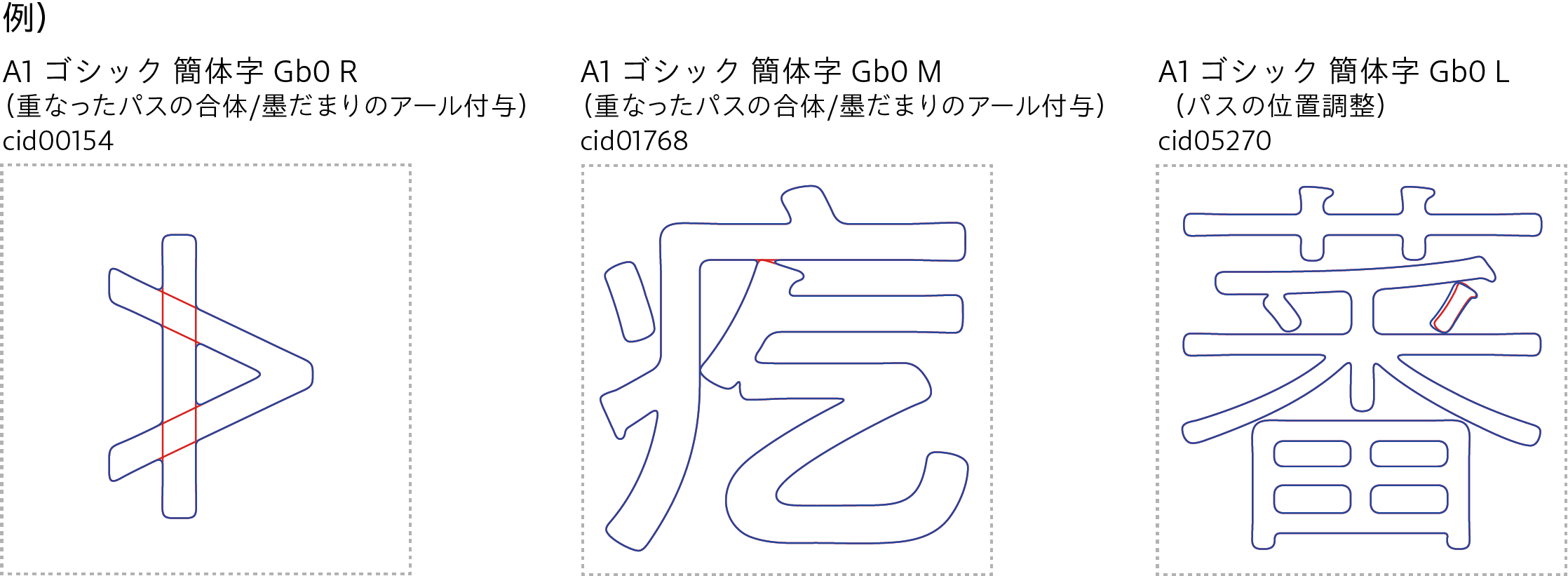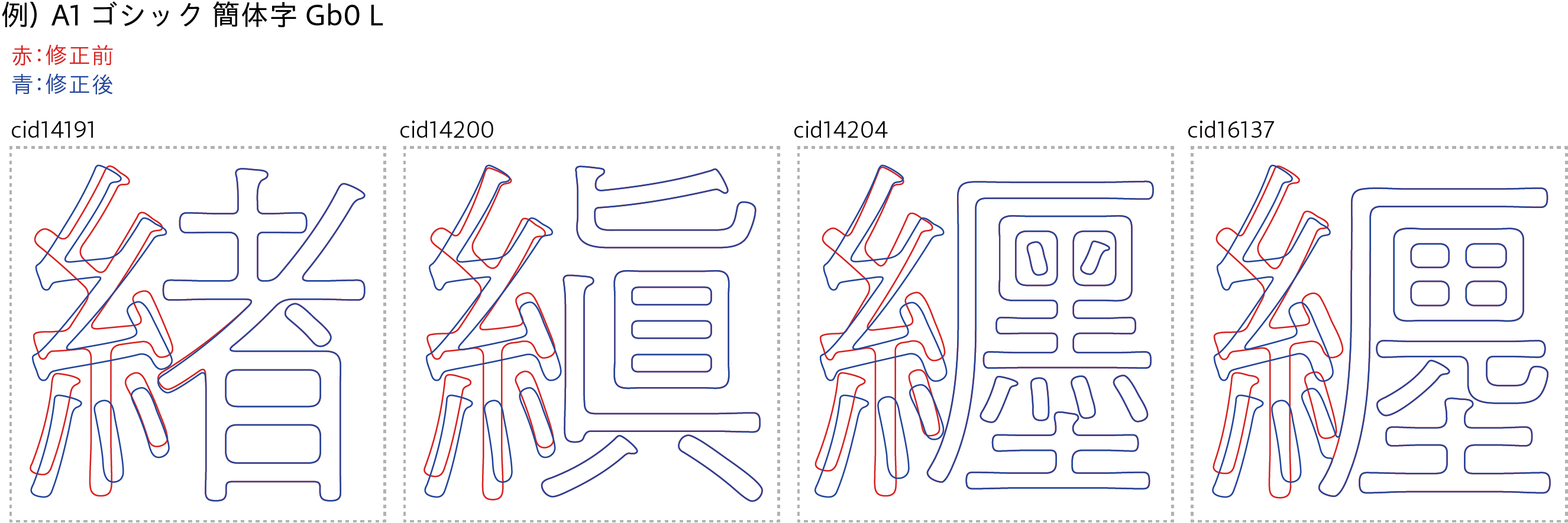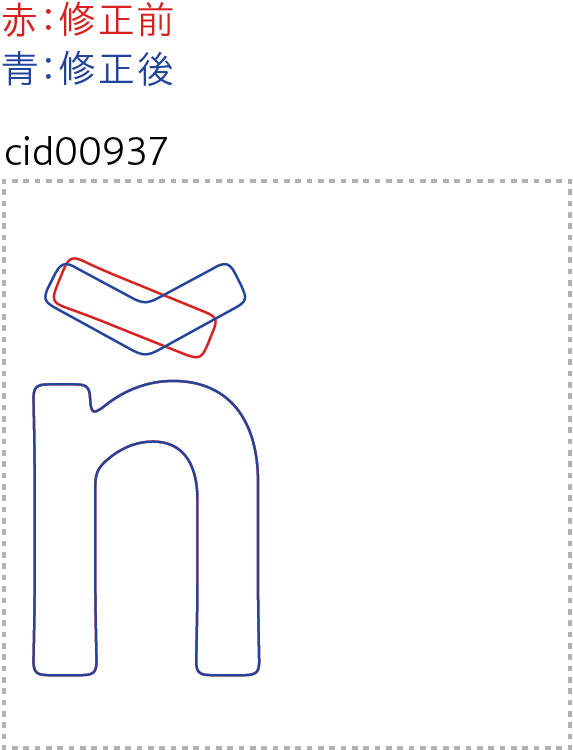
1. A1ゴシック 簡体字
字幅・誤字・アウトラインの修正があります。
改訂内容
【1】字幅の修正
全角幅が全角基準よりわずかに大きい1001となっていたため、1000(全角)に修正を行いました。
【2】誤字の修正
字形に誤りがあったため、修正を行いました。
【3】アウトラインの修正
重なったパスの合体・墨だまりのアール付与・パスの位置調整など、アウトラインの修正を行いました。
※墨だまりのアール付与とは、複数のパスを合体したときにできる角の部分に、A1ゴシック特有の丸み(アール)を加える処理のことです(参考:温もり感じるゴシック体「A1ゴシック」)。
2. A1ゴシック 繁体字
字形の変更・アウトライン処理の修正があります。
改訂内容
【1】字形の変更
「いとへん」の字形を他の文字と統一しました。
【2】アウトラインの修正
重なったパスの合体・墨だまりのアール付与・パスの位置調整など、アウトラインの修正を行いました。